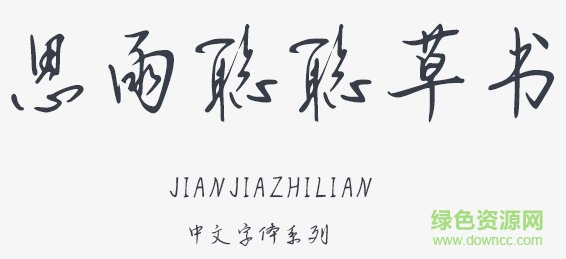
思雨聰聰草書體是思雨字體庫中全新上線的一款草書字體,文風(fēng)飄逸灑脫,極具古風(fēng)字體的藝術(shù)美感,結(jié)構(gòu)大氣造型精簡,自己連貫而不凌亂,有著極佳的視覺體驗(yàn),快來綠色資源網(wǎng)試試吧!
思雨聰聰草書體下筆有神韻,落筆從容而淡定,適當(dāng)?shù)倪B寫讓文字盡顯沉穩(wěn)干練的書法毛筆書法字體韻味,給人凌然正氣、瀟灑不羈的藝術(shù)效果,可以廣泛運(yùn)用在藝術(shù)設(shè)計(jì)、包裝設(shè)計(jì)、平面設(shè)計(jì)等多種領(lǐng)域!
草書藝術(shù)的美體現(xiàn)在兩個(gè)方面:即表層的外形美和深層的蘊(yùn)涵美。也有人將草書藝術(shù)的美概以十點(diǎn):曰點(diǎn)劃飛動(dòng),曰筆情墨趣,曰結(jié)體多變,曰章法生動(dòng),曰線條優(yōu)美,曰血脈連通,曰氣韻天成,曰轉(zhuǎn)化跌宕,曰氣勢磅礴,曰奇逸瀟灑??傊輹囆g(shù)之美宛若無言而有詩篇之意蘊(yùn),無動(dòng)而有舞蹈之神形,無色而有繪畫的斑斕,無聲而有音樂的旋律。